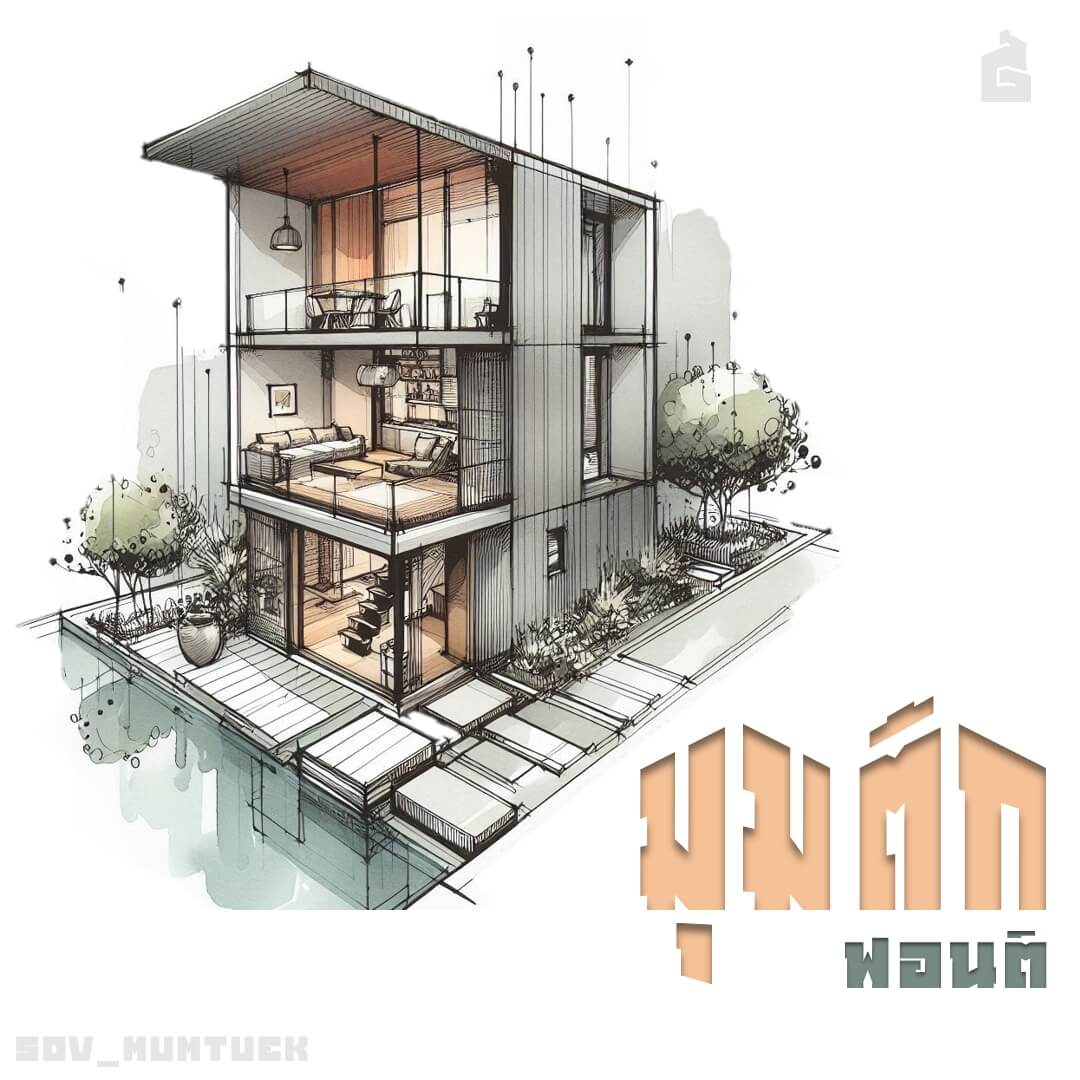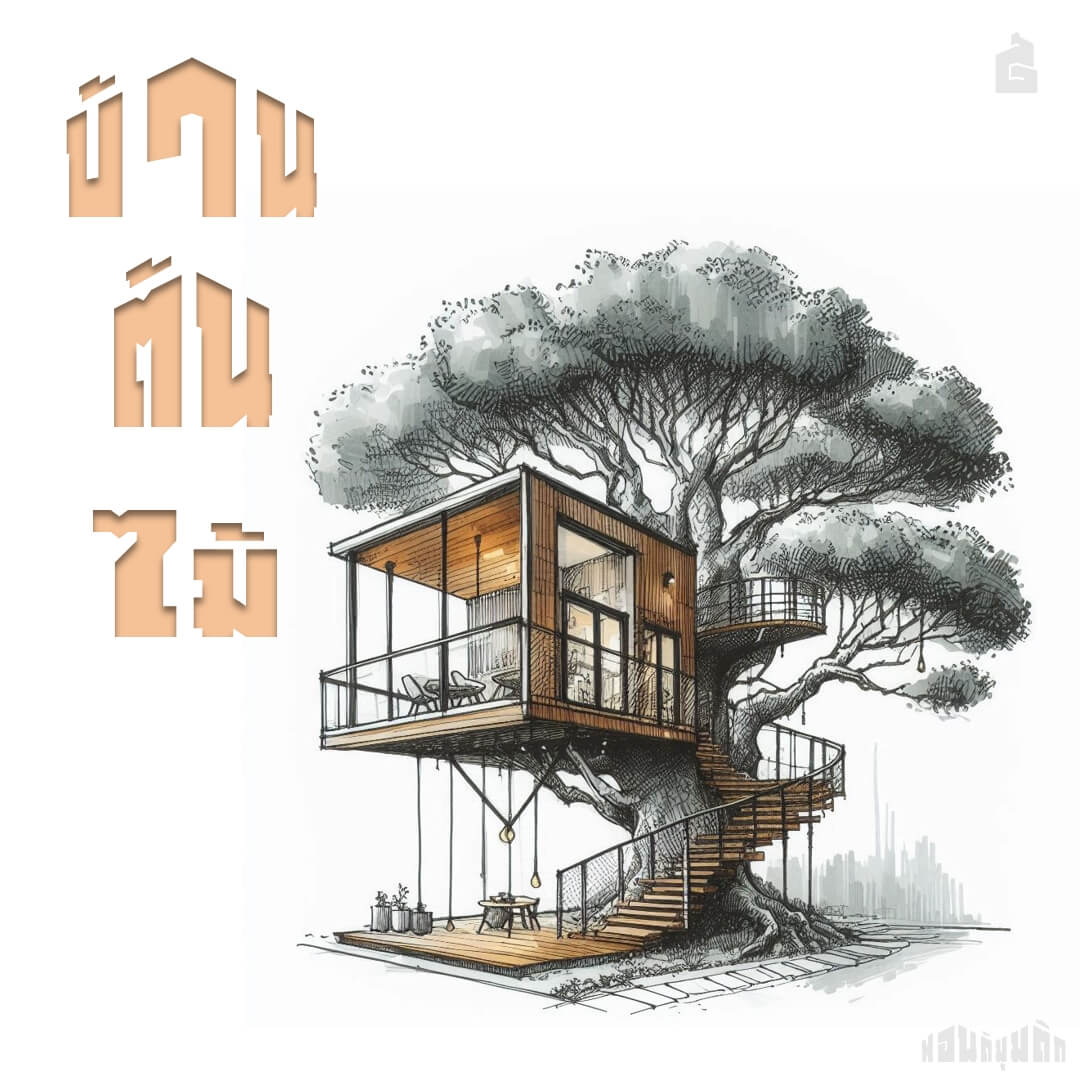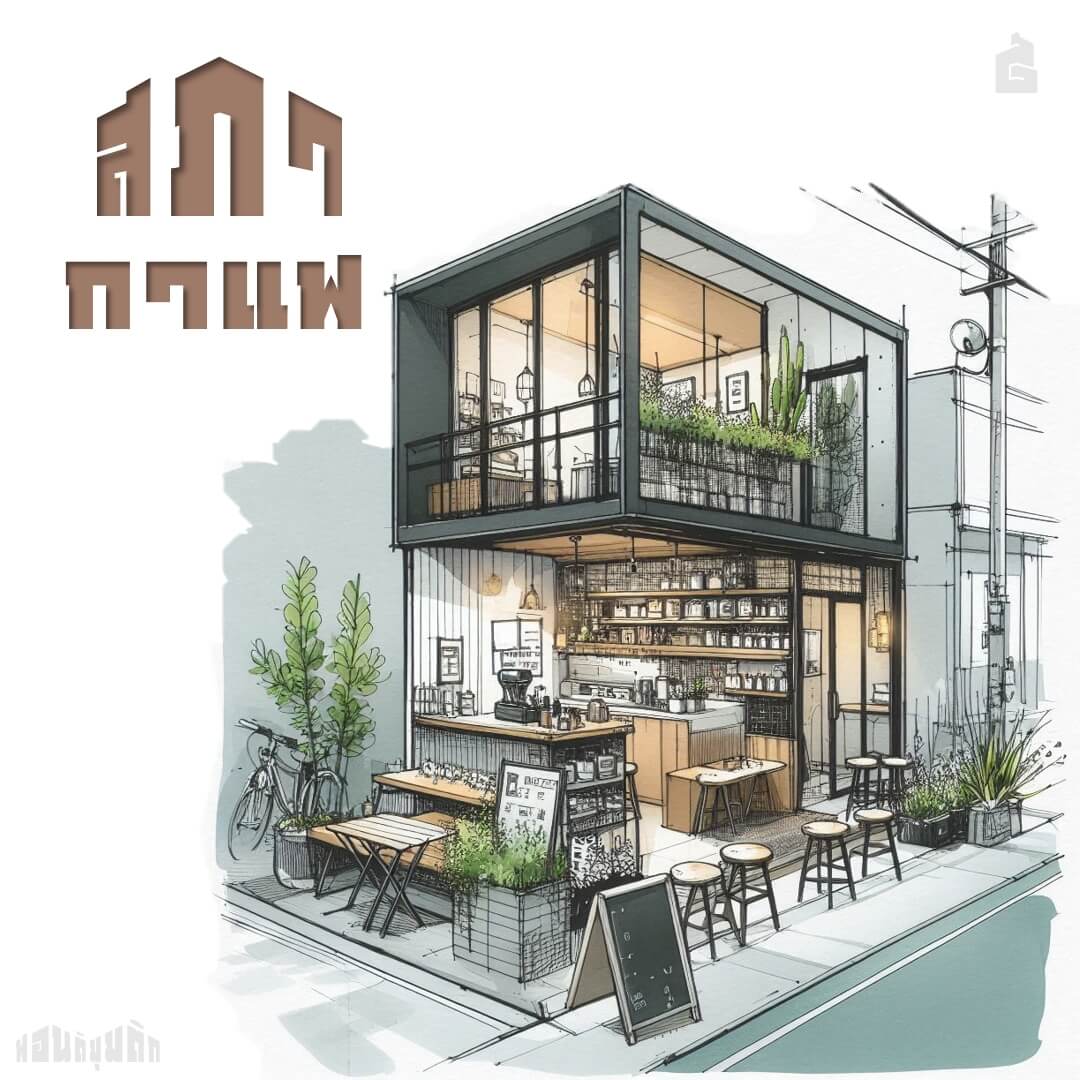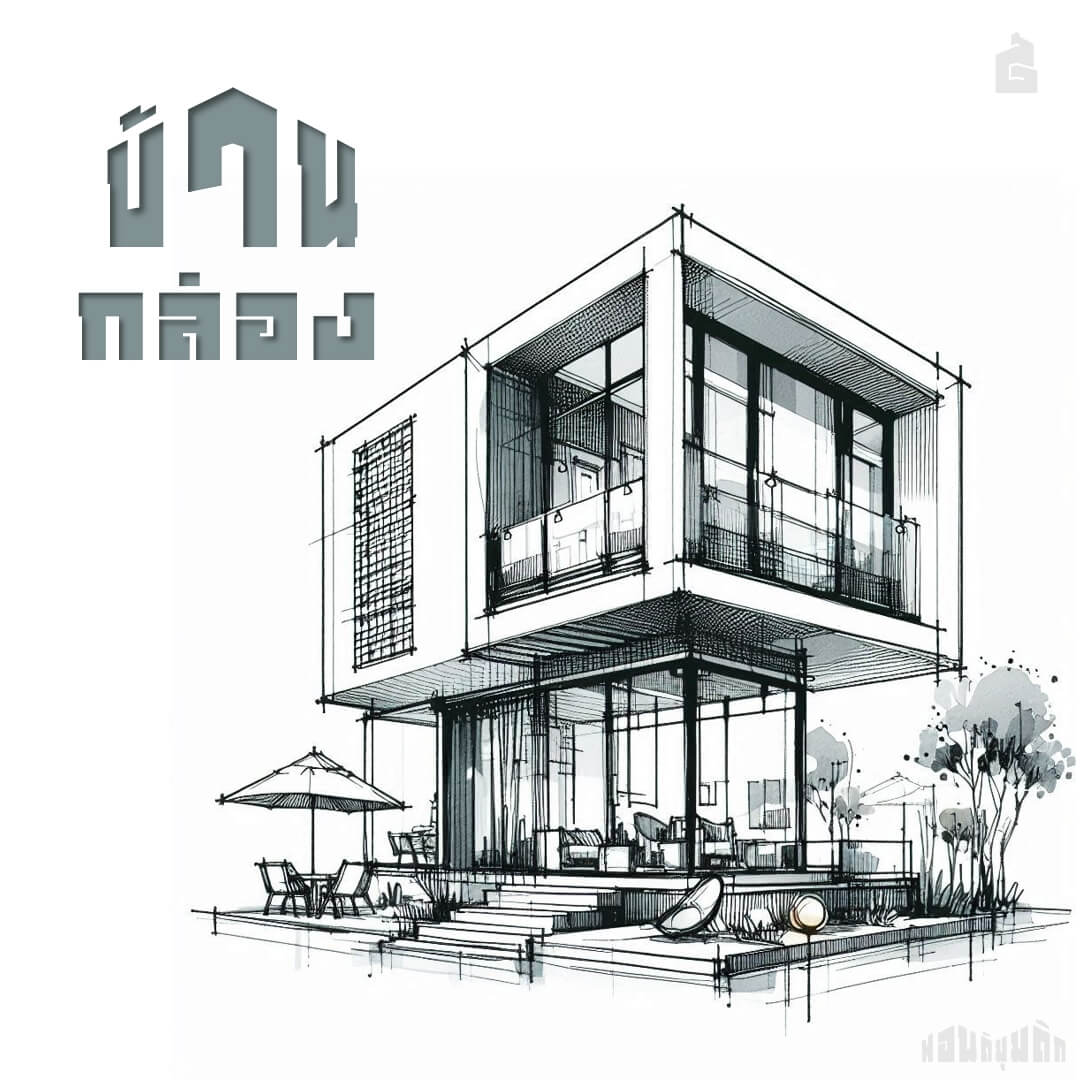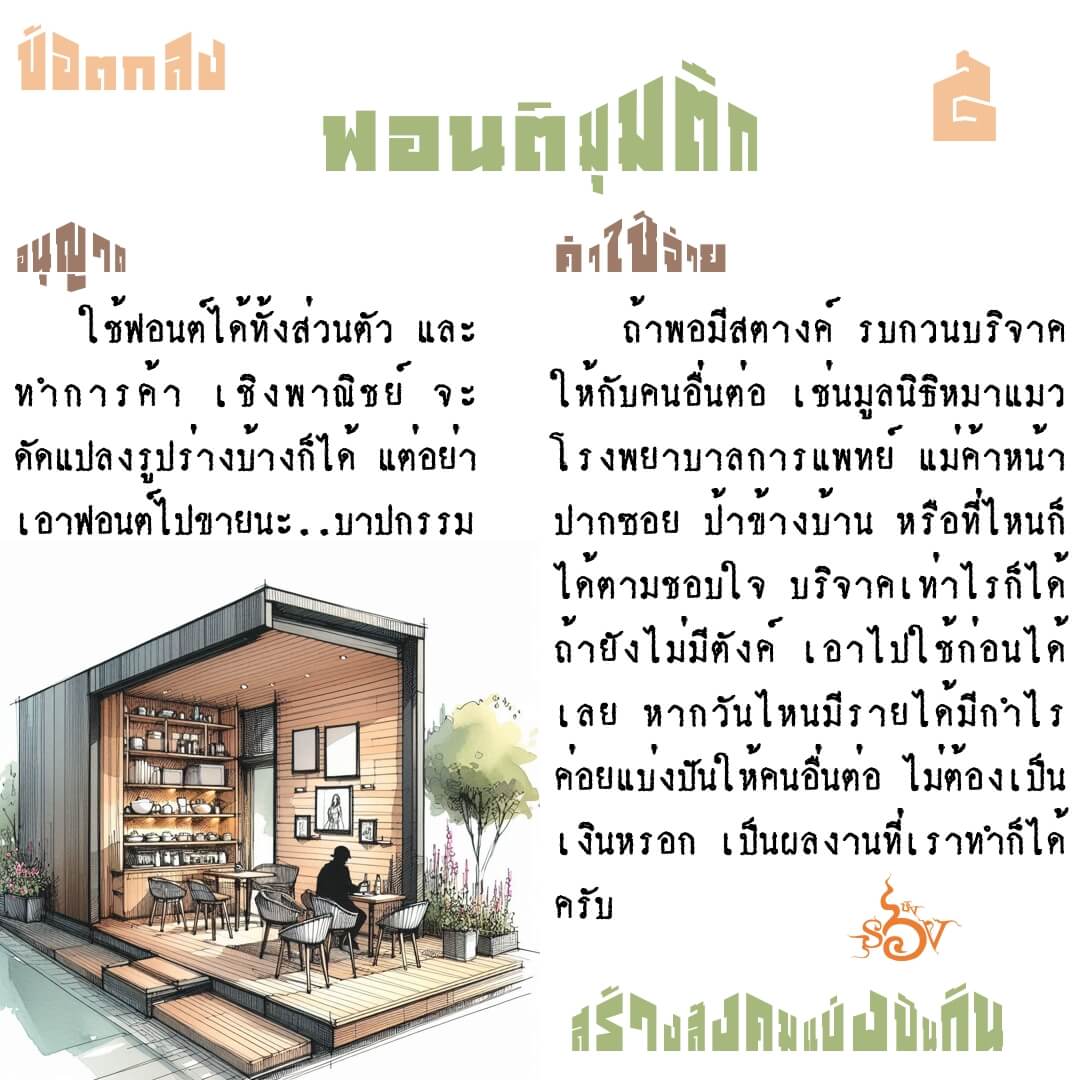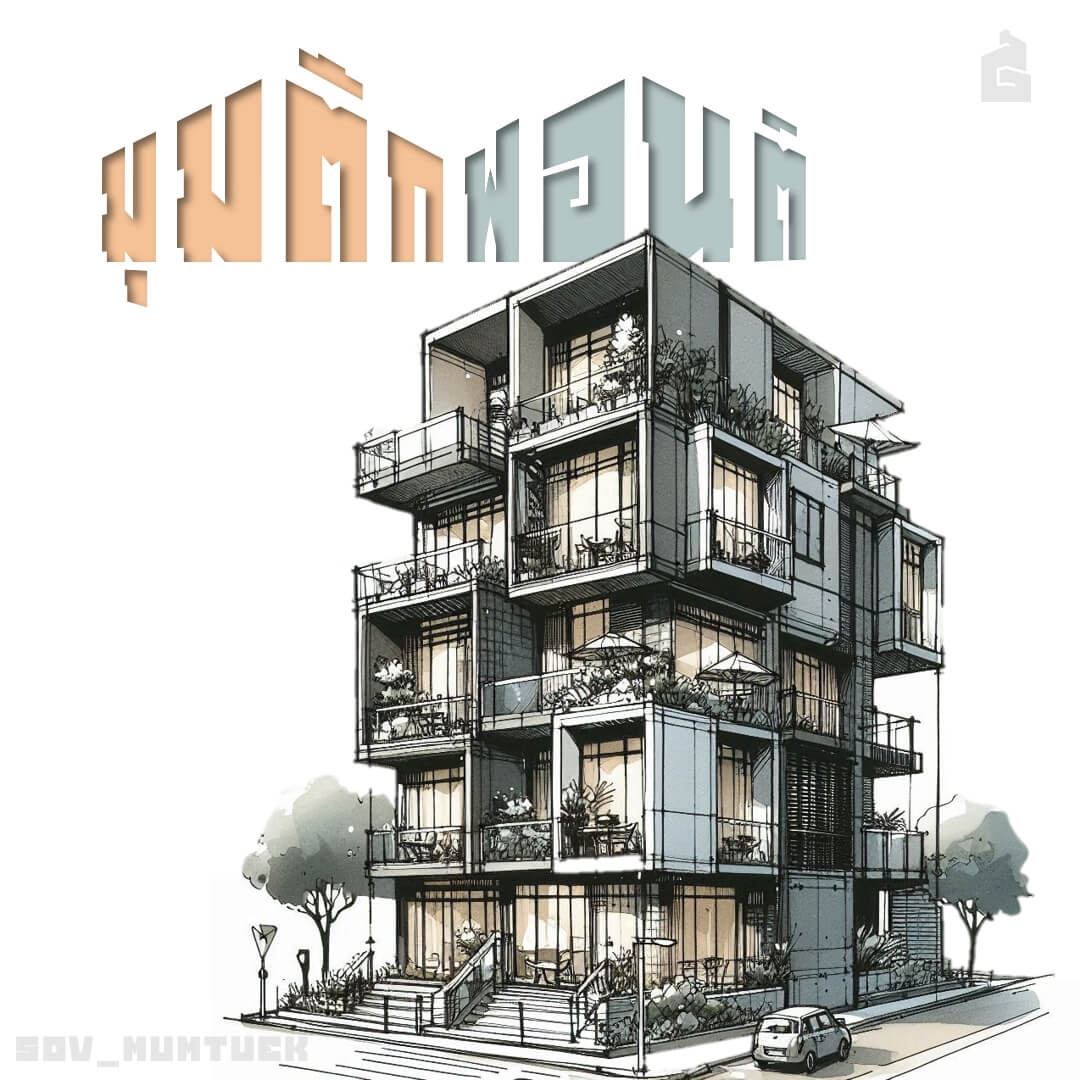
มุมตึก (SOV_MumTuek)
ฟอนต์มุมตึก – เป็นแนว logo รูป perspective มุมเงย สำหรับอักษร 2-5 ตัว (กรณีเขียนเป็นประโยค ให้เคาะ space แยกคำ)
เบื้องหลังการออกแบบ : ฟอนต์ มุมตึก